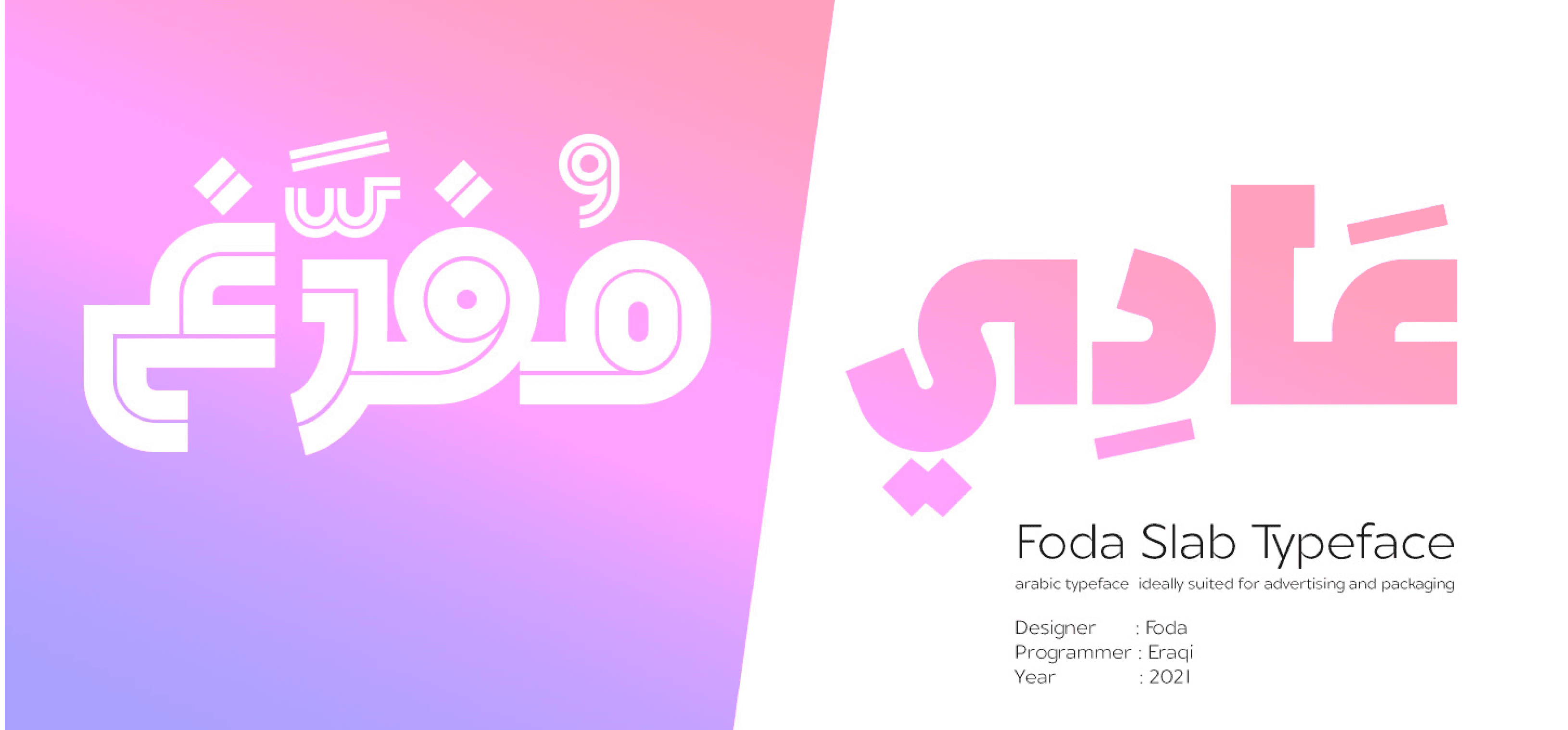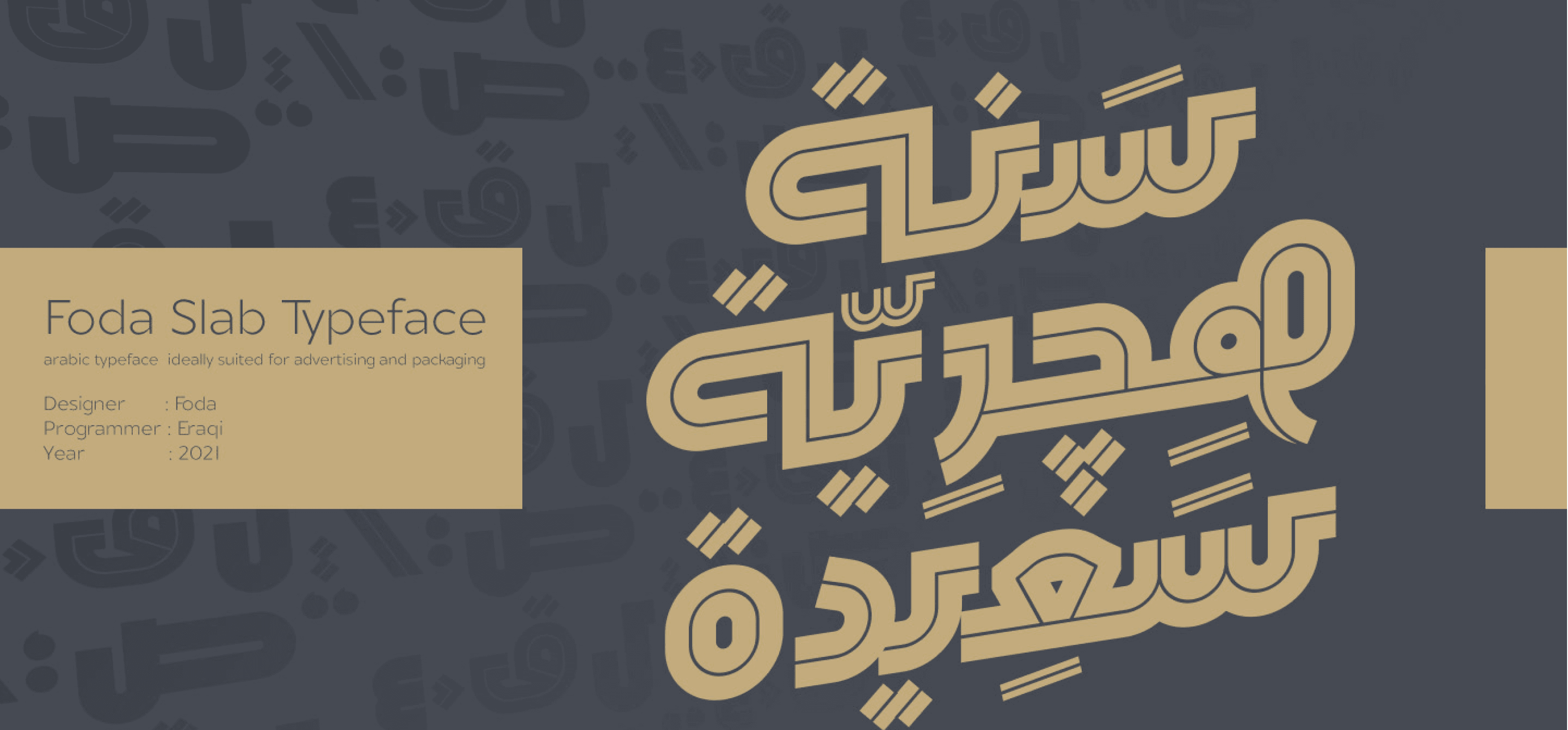
خط Foda Slab هو خط سلاب عربي قوي، يأتي بنمطين: عادي (Regular) ومجوف (Hollow).
يحتوي على 886 رمزًا (Glyph)، ويتضمن العديد من التراكيب (Ligatures)، مما يجعله مناسبًا للعناوين والسياقات التصميمية المختلفة.